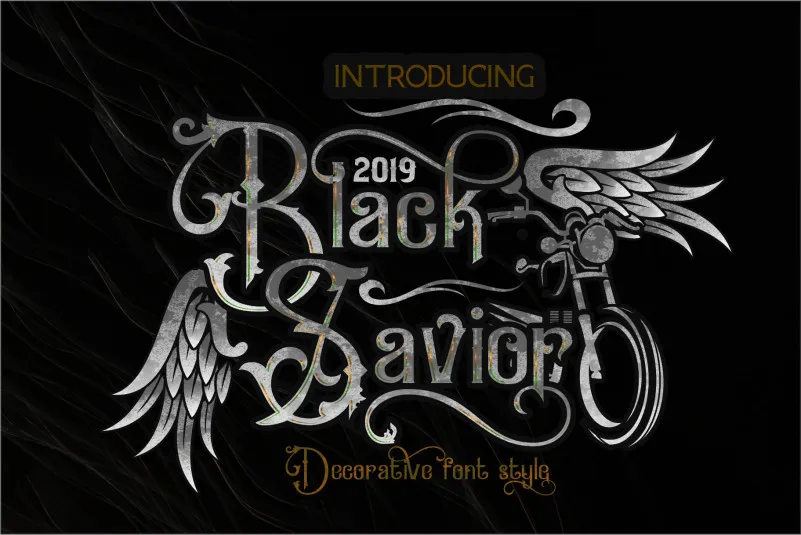
Black Savior Victorian Retro Font – Download Grátis
A Black Savior Victorian Retro Font é uma elegante opção para quem busca adicionar um toque retrô e sofisticado a seus projetos digitais, especialmente aqueles com temas vintage ou antigos. Esta fonte de exibição se adequa perfeitamente às criações que valorizam elementos únicos e clássicos, inspirada em fontes antigas, desenhos decorativos e até mesmo elementos florais. Com a característica OpenType, esta elegante fonte adiciona um toque distintivo e sofisticado ao seu design. Perfeita para quem busca uma transição suave do moderno para o clássico ou aqueles que valorizam retrôs com um toque de originalidade. Seja em logotipos, designs de site ou até mesmo em e-mail marketing, a Black Savior Victorian Retro Font é uma escolha inteligente para qualquer designer que deseje agregar profundamente esse elemento retro na sua marca.